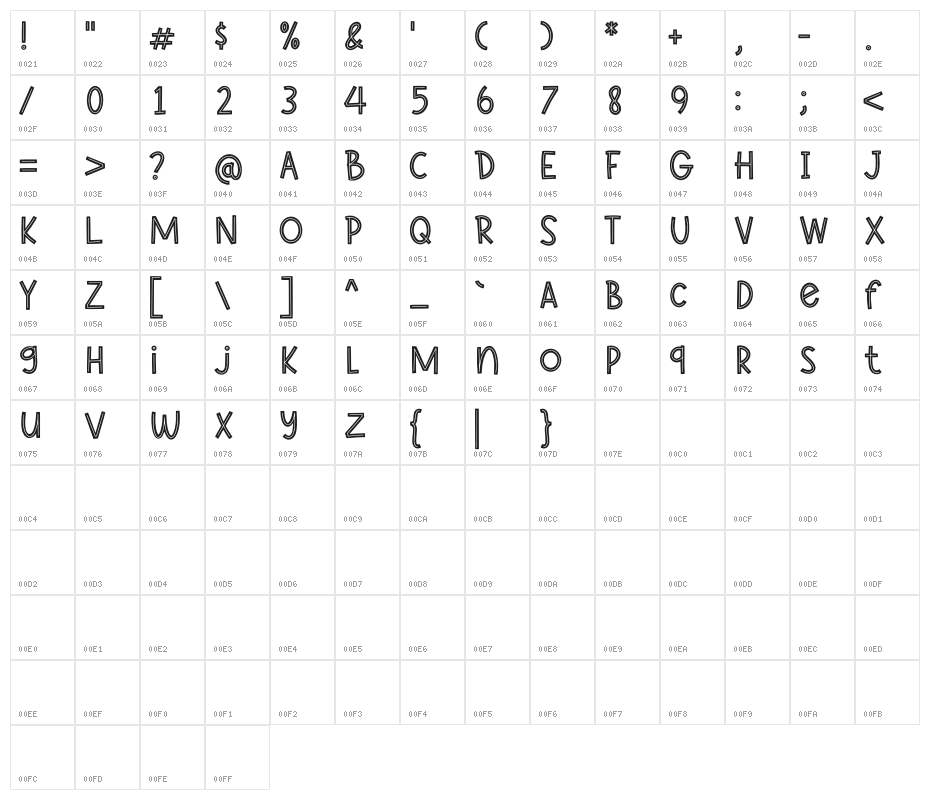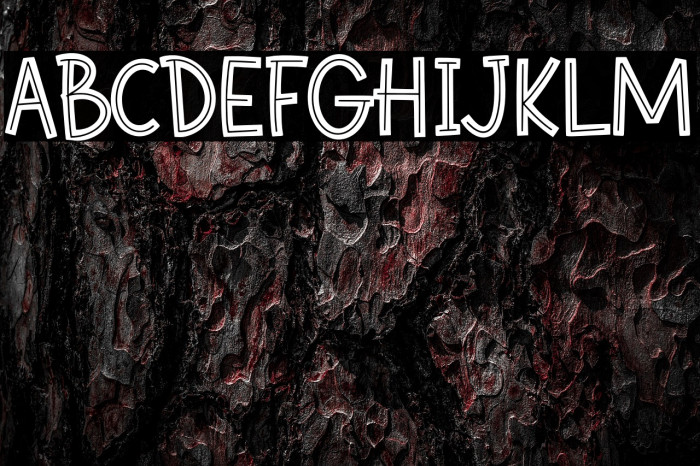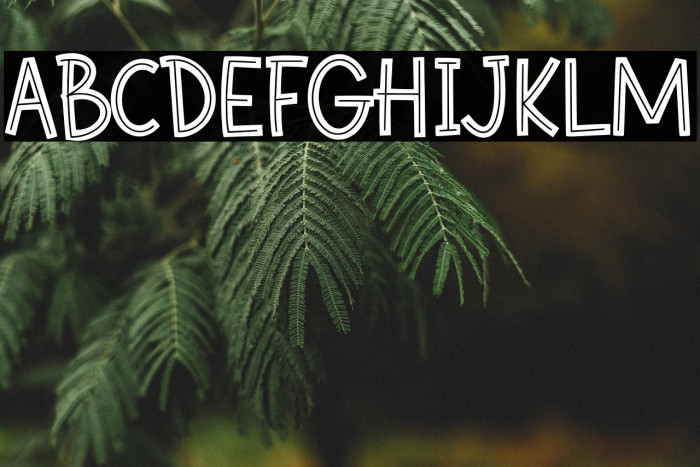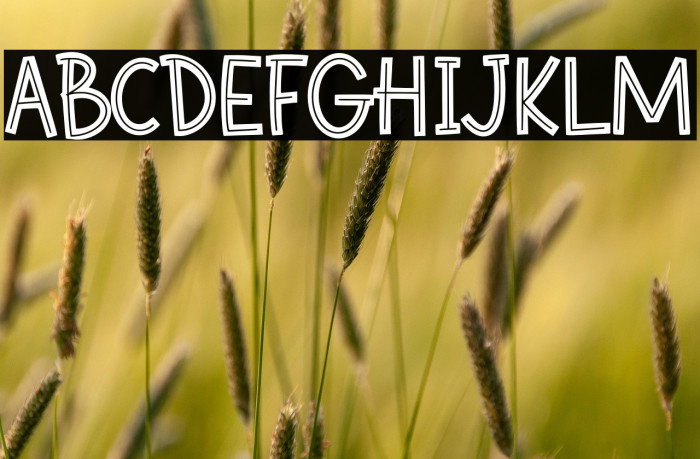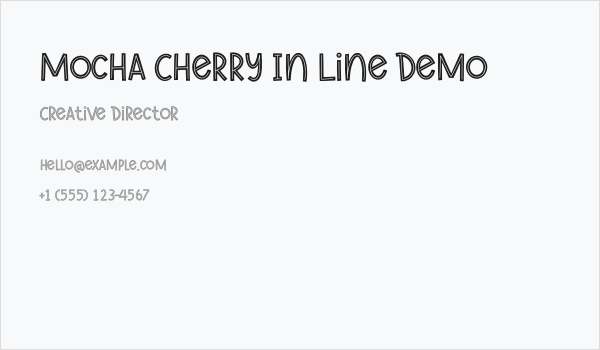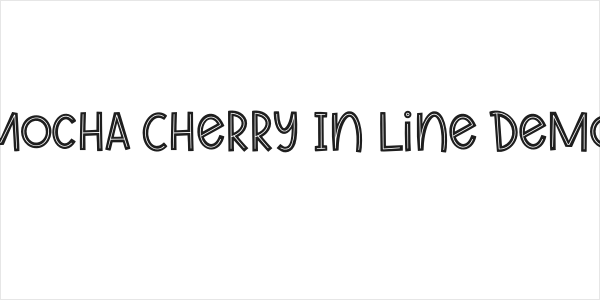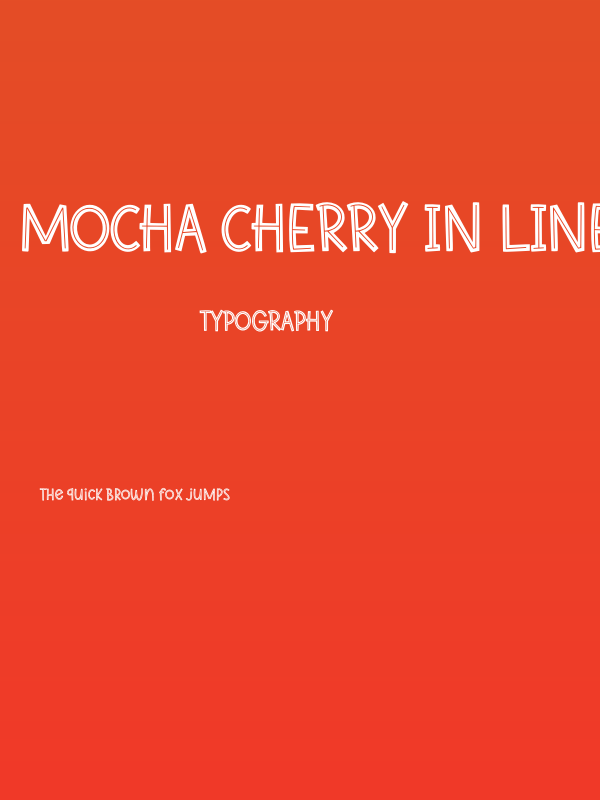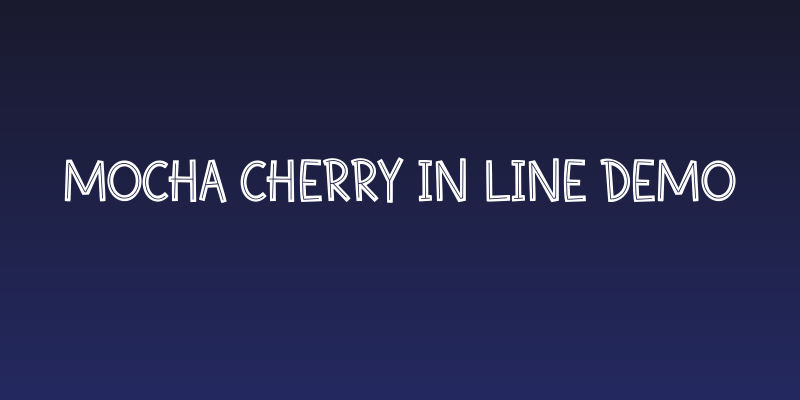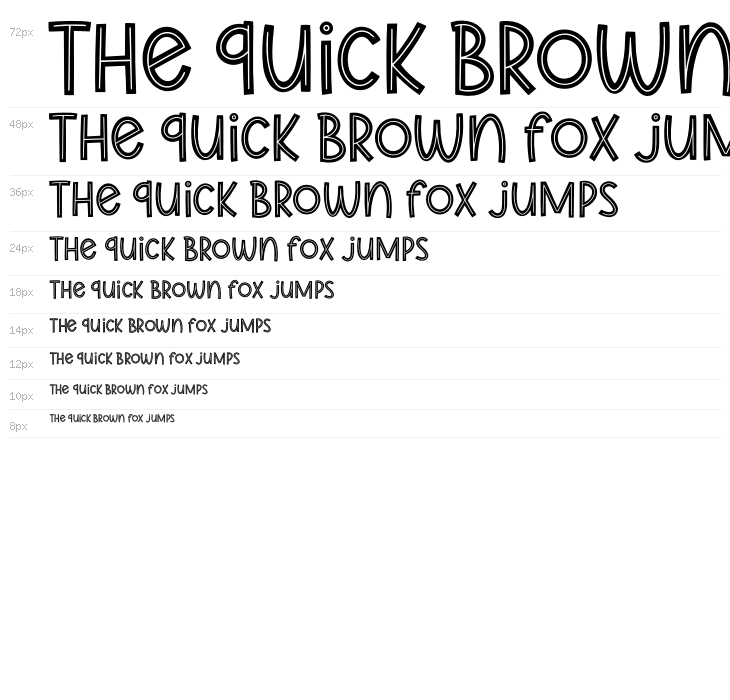
Mocha Cherry In Line Demo Font
| Stile generale | Playful, Whimsical, Hand-drawn |
| Caso d'uso | Headlines, Posters, Creative Projects |
| Progetti proposti | Ideal for children's books, playful branding, posters, and creative invitations. |